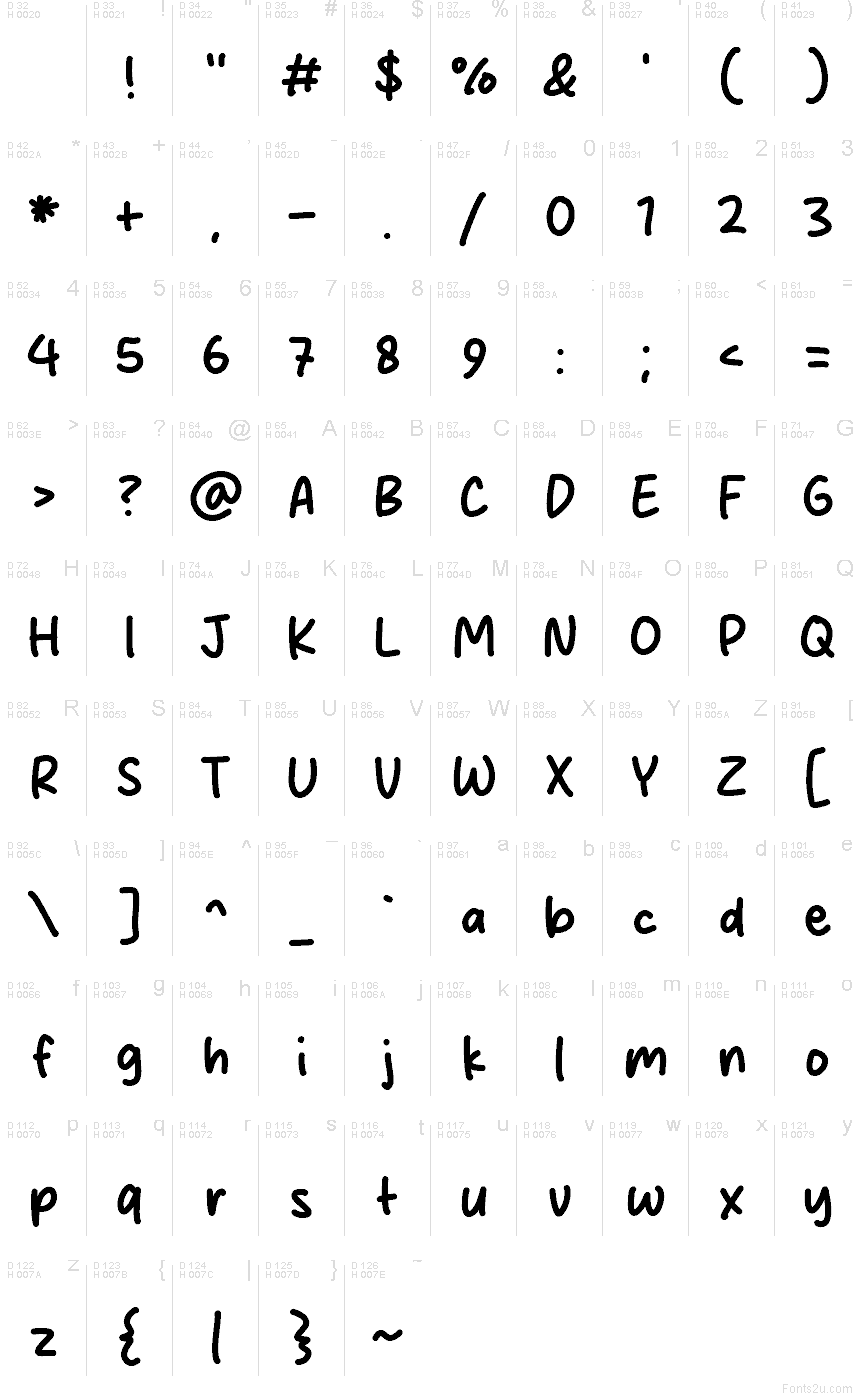
Cheese Milky par MJType est une police manuscrite gratuite, dotée d'une personnalité douce, rebondie et d'une ambiance rétro décontractée. Les lettres semblent avoir été coulées plutôt que dessinées, avec des traits épais et arrondis, des courbes généreuses et un rythme légèrement irrégulier qui confère à ce style un côté humain et chaleureux.
Elle est idéale pour le packaging, l'identité visuelle de cafés, les étiquettes de produits alimentaires, les cartes de vœux et les réseaux sociaux où une police gratuite peut apporter une touche artisanale sans paraître artificielle. Utilisez-la pour vos titres courts, vos ébauches de logos ou vos textes de couverture lorsque vous souhaitez une approche douce et accessible : ses formes charnues donnent du relief et de la vitalité, même aux textes les plus courts.